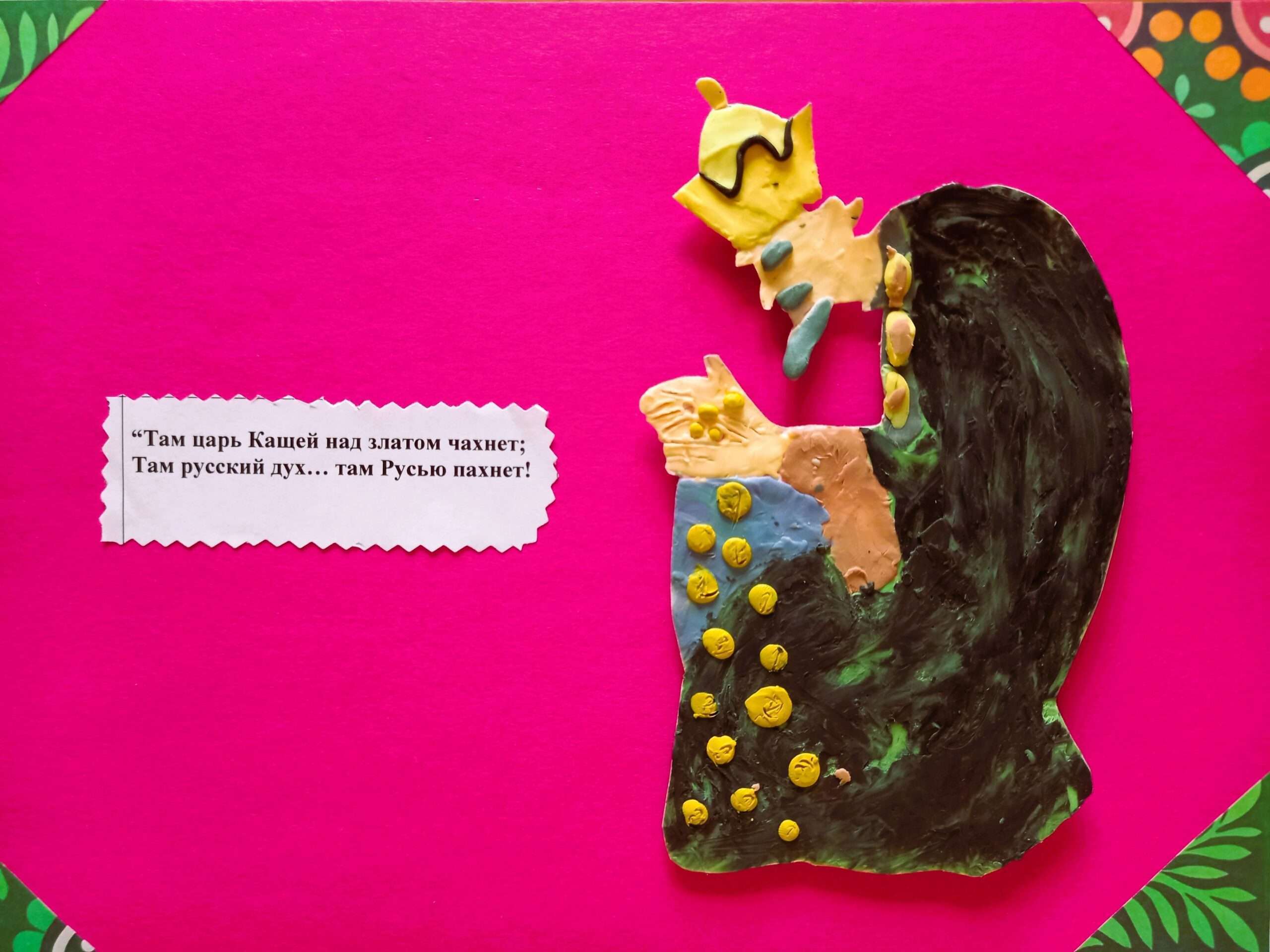
Буква З. Шрифт Пушкиненок.
Буква изображена в виде героя из сказки А. С. Пушкина. Выполнена в стиле пластилинография. Сопровождение: цитаты из сказок. Это веселая игра со сказкой. Так я вижу мир букв.